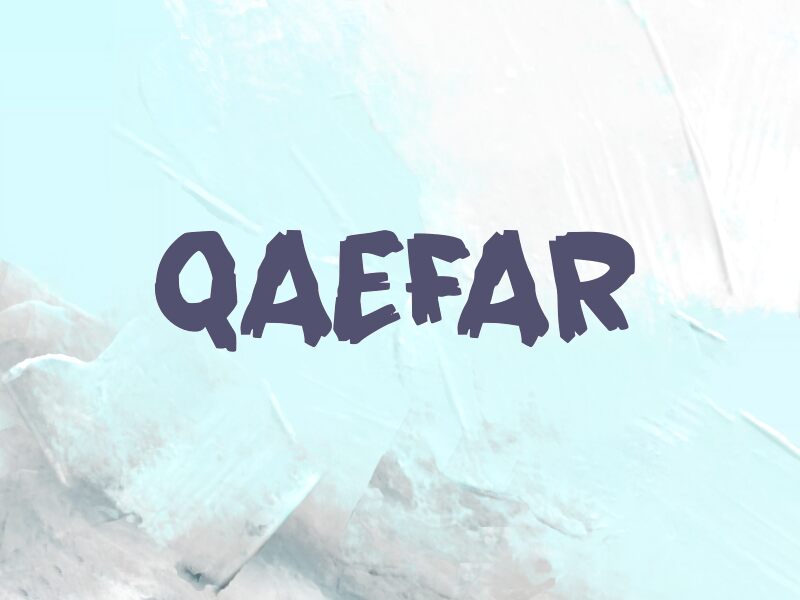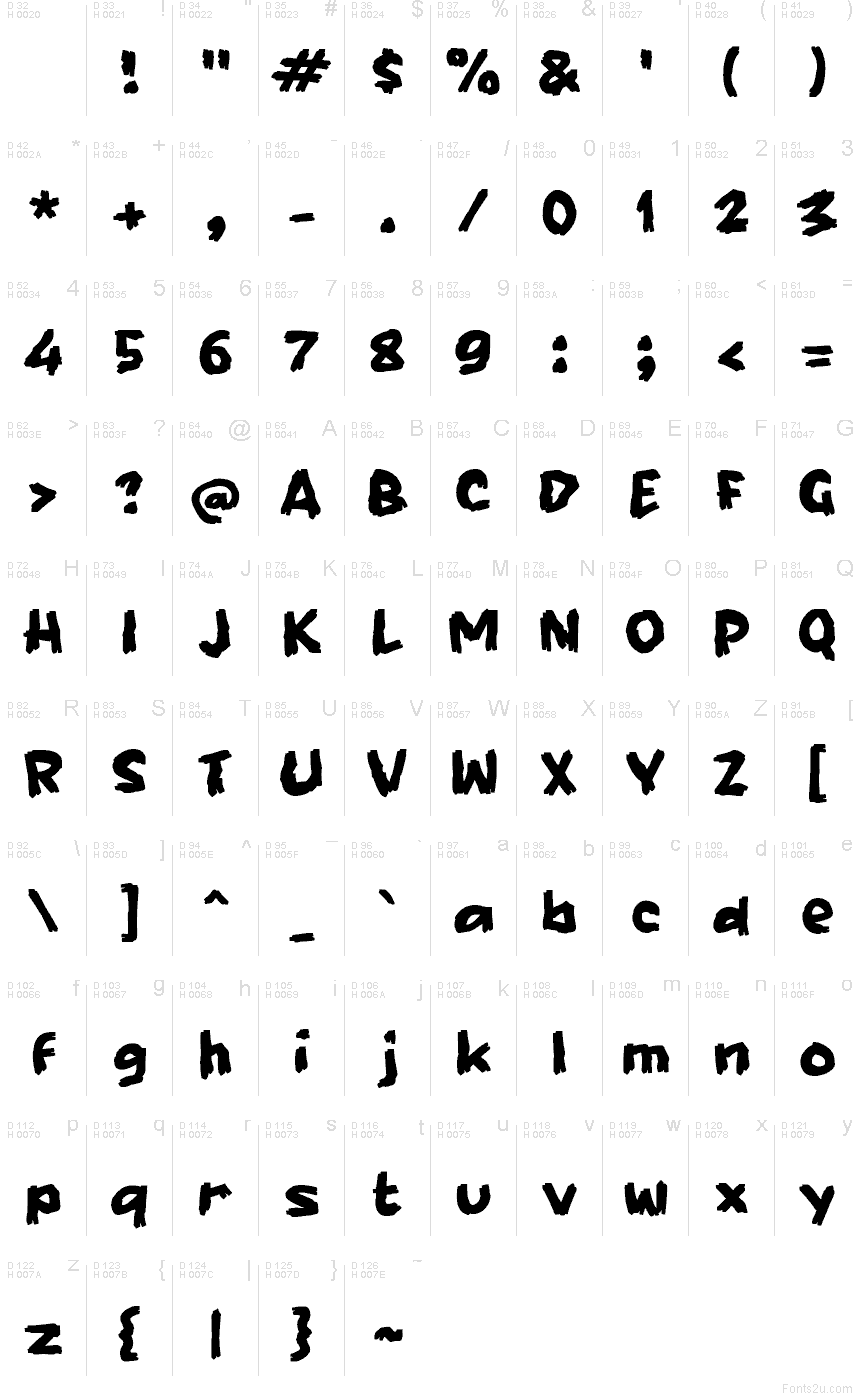
QAEFAR
Qaefar di Wep è un font a pennello gratuito, ruvido e dal carattere fortemente artigianale. Le lettere sembrano tracciate con una pennellata carica di colore: tratti spessi, bordi irregolari e giunzioni imperfette che conferiscono all’intero set un’energia da poster urbano, ben lontana dalla levigatezza di un lettering professionale.
Si adatta perfettamente a grafiche streetwear, flyer musicali, copertine a tema horror, titoli di giochi e testate d'impatto sui social, dove questo font gratuito può regalare un tocco crudo e "fatto a mano". Usalo quando vuoi che parole brevi, monogrammi o loghi risultino graffianti e fisici; le forme a cuneo ricorrenti e la silhouette vissuta assicurano che il font mantenga la sua potenza anche in poche lettere.